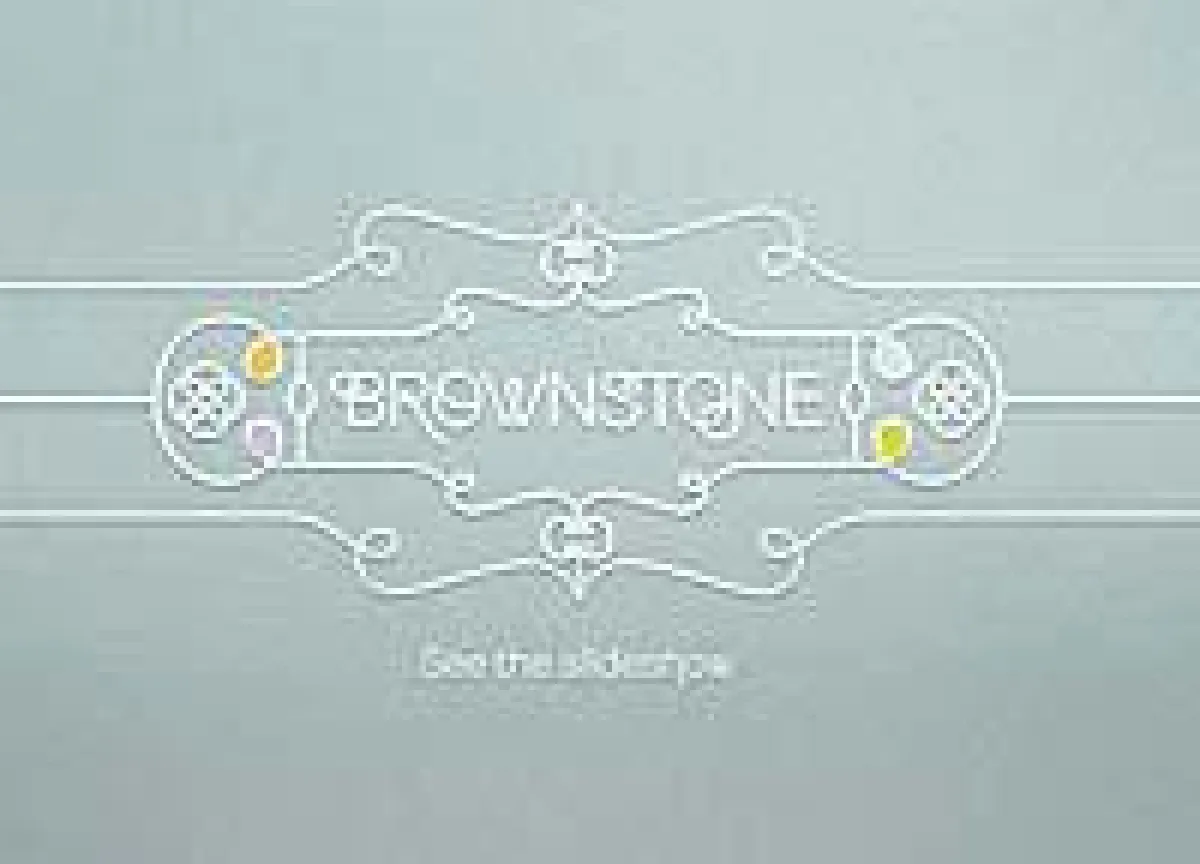
Veer gibt Veröffentlichung neuer Schriftarten und Auszeichnungen bekannt
(openPR) Veer nimmt zahlreiche neue Schriftarten in die umfangreiche Kollektion auf und gibt die Verleihung von Auszeichnungen an Schriftdesigner bekannt
Berlin, Juni 2010 – Veer (veer.com), Hersteller und Anbieter preisgünstiger visueller Elemente und designbezogener Produkte, erweitert sein Angebot an preisgünstigen und kunstvoll gestalteten Schriftarten. Auerßdem wurden zahlreiche neue Schriftkollektionen und einzelne, exklusive Schriften ins Portfolio aufgenommen.
TypeTogether, eine zur Nutzung durch Verlage und Unternehmen bestimmte Kollektion qualitativ hochwertiger und detailreicher Schriftarten, wurde um vier Schriften erweitert: Etica, Rue, Edita Small und Skolar. Etica ist eine von dem renommierten italienischen Designunternehmen LeftLoft entwickelte serifenlose Schriftart. Der Stil dieser ebenso starken wie wandelbaren Schriftart liegt irgendwo zwischen grotesk und humanistisch. Sie vereint in sich männliche Stärke und feminines Feingefühl, weiche Linien und offene Punzen. Edita Small ergänzt die Edita-Familie um vier neue Schriftarten, die speziell für sehr kleine Schriftgrößen entwickelt wurden.
Darüber hinaus wurden unter anderem folgende neue Kollektionen und Schriftarten hinzugefügt:
• Brownstone – Die einlinige, serifenlose Schriftart wurde von Alejandro Paul exklusiv für Veer entworfen. Für die weichen, verschnörkelten Formen seines neuen Meisterwerks ließ sich der Designer von den historischen Gebäuden aus braunem Sandstein (engl. Brownstone) in Brooklyn, New York, inspirieren. Brownstone wird Teil der Umbrella-Kollektion. Die eher technisch anmutenden Buchstabenformen verbinden sich mit dekorativen Rahmen und verschnörkelten Formen zu einer gelungenen Mischung aus Alt und Neu. Diashow ansehen.
• Ebenfalls neu in der Umbrella-Kollektion ist Facetype Foundry, die mit neun neuen Schriftfamilien ihren Einstand gibt. Facetype, das 2008 von Marcus Sterz und Andrej Waldegg gegründete Unternehmen, hat sich auf kreative Schriftarten spezialisiert und experimentiert dabei oft mit mehreren übereinanderliegenden Elementen und Farben.
• Die Alphabet-Kollektion wurde von der amerikanischen Popkultur des 20. Jahrhunderts inspiriert. Die Schriftarten von Michael Doret, Gründer des Fontlabels Alphabet Soup , erinnern an Streichholzbriefchen, Theatermarkisen, Emaille-Schilder und Verpackungen aus den 50er Jahren. Seine Arbeiten wurden bereits im Time Magazine sowie auf dem Cover des KISS-Albums „Rock and Roll All Over“ verwendet.
• Dunwich Type Founders – diese Kollektion wurde von James Phuckett entworfen. Seine neueste Schriftfamilie Armitage umfasst 12 serifenlose Schriftarten, die mit ihren asymmetrischen Linien und der zurückhaltenden Ausbauchung an beliebte amerikanische Schriftarten des späten 19. Jahrhunderts erinnert. Außerdem nimmt Veer die Schriftarten Downturn, Black Monday und Recovery in die TypeTrust-Kollektion auf.
Mit großem Stolz gibt Veer die Verleihung folgender Auszeichnungen an Schriftdesigner bekannt:
• Der neueste Entwurf für Veer von Alejandro Paul, Brownstone, wurde auf der alle zwei Jahre stattfindenden Ausstellung „Tipos Latinos 2010“ in Montevideo, Uruguay, mit einem „Certificate of Excellence“ ausgezeichnet. Von den 448 Beiträgen erhielten nur sechs weitere Schriftarten die höchste Auszeichnung des Komitees.
• Bei den diesjährigen „Type Directors Club Annual Awards“ wurden unter 176 Beiträgen zwei Schriftarten von Veer ausgewählt: Deliscript von Michael Doret und Fugu von Neil Summerour.
„Schriftarten bringen es heute zu immer größerer Beliebtheit, denn die Designer finden kreative Wege, ihre Entwicklungen über Printmedien oder das Internet bekannt zu machen.“, so Joe Newton, Product Manager Type bei Veer. „Mit Neuzugängen wie FaceType und Dunwhich Type Founders werden wir unseren Kunden künftig eine noch größere Auswahl ganz spezieller Schriftarten bieten können.“